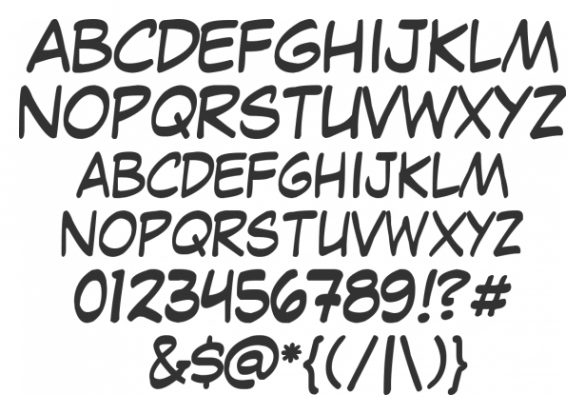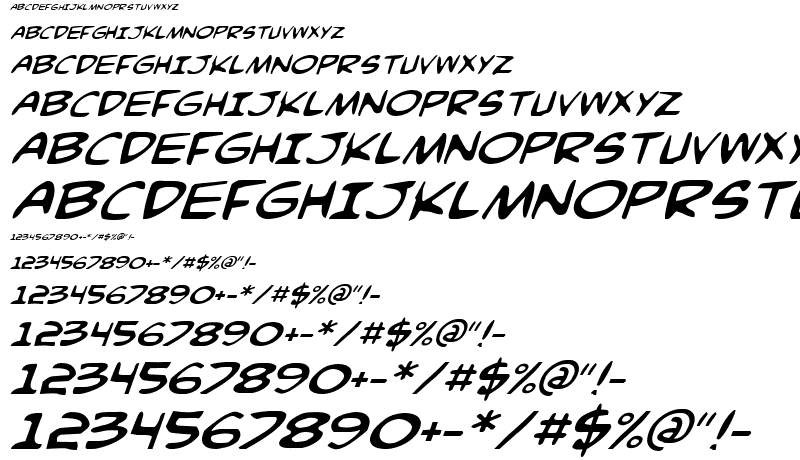
Лучшие шрифты с поддержкой кириллицы для Манги: список
Мы подобрали для вас самые известные 🔝 и популярные шрифты для манги. 📖 Именно эти шрифты используются многими переводчиками 📢 в течение длительного времени, и многие пользователи узнают их 👀 по внешнему виду.
Шрифты для манги или комиксов востребованы всегда. И сколько лет уже существует в интернете направление по переводу манги, столько же есть и вариантов шрифтов.
Хотя зачастую для основных надписей используют всегда одни и те же шрифты, т.к. их читать удобно и выглядят они стильно. Но, например, мысли, восклицания, надписи сюжета, бывает, что пишут разными. Что же до тех художников, кто рисует мангу или комиксы для себя – они используют шрифты разные, те, что ближе по духу и атмосферности.
Шрифт Aqum 2 кириллица
Aqum 2 семья шрифтов из 4 стилей.
Шрифт Bondi кирилица
Шрифт Storytella Cyrillic
Golos
Golos Text — универсальный закрытый гротеск, хорошо подходит для чтения длинных текстов с экрана и рекомендуется для государственных сайтов и социальных сервисов. Golos UI — униширинный гротеск, который благодаря чуть зауженным пропорциям, идеально подходит для использования в элементах интерфейсов. Свойство фиксированной ширины знаков (Uniwidth) позволяет сохранять длину строки, при работе с начертаниями разной насыщенности.
Дизайнеры Александра Королькова и Виталий Кузьмин. Шрифт подготовлен и выпущен компанией Паратайп в 2019 году. Количество глифов 467.
Lack
Это смелый, современный и экспериментальный шрифт, который поставляется в одной насыщенности с курсивом. Он хорошо работает как дисплейный шрифт, но также предназначен для работы с текстами любого размера.
В 3 различных стилистических наборах спрятано множество альтернатив. VTFLack был первоначально создан Адриеном Мидзиком в 2013 году. В 2016 году он начал перерабатывать шрифт, чтобы его можно было использовать в разных графических областях, а не только для экспериментальных работ.
В этой версии есть оригинальные строчными буквы, оптимизирована разборчивость и добавлены контурные начертания. Последнее обновление 2018. Количество глифов 1017.
Bebas Neue
Бебас — самый популярный во всем мире прописной шрифт стал «Гельветикой свободных шрифтов». Выпущенный в 2010 году Bebas Neue используется как крупными компаниями, так и начинающими дизайнерами для многих проектов. Новые начертания остаются верными стилю и изяществу Bebas со знакомыми чистыми линиями, элегантными формами, сочетанием технической прямоты и теплой простоты. Семейство Bebas Neue одинаково уместно для веб, печати, коммерции и искусства.
Ему делают регулярные обновления, а в 2019 вышел долгожданный платный Bebas Neue Pro со строчными буквами и наклонными начертаниями.
Moniqa
Вариативный шрифт с 162 начертаниями разной ширины и контрастности. Начертание Display (с самыми тонкими элементами и сильным контрастом) выглядит изящно и богато в крупном размере, Heading подойдет для заголовков, а Paragraph обладающий наименьшим контрастом — для более мелкого текста. Это многоязычный шрифт с альтернативными символами, стилями, лигатурами и множеством возможностей OpenType.
Идеален для журналов, рекламы и брендинга. Дизайнер Rajesh Rajput. Опубликован на Behance 4 июня 2019 года. Количество глифов 865.
Spectral
Текстовый шрифт, обращающийся к истории французского шрифтового дизайна, но современный и универсальный, хорошо подходящий для чтения с экрана: Spectral разрабатывался в первую очередь как шрифт для Google Docs и Google Sheets — офисных инструментов для совместной работы.
У него характерные для динамической антиквы контраст, открытость знаков и оси овалов. Есть ещё родственный капительный шрифт Spectral SC с таким же набором начертаний.
Кириллица в шрифте качественная и сбалансированная, с хорошо применёнными конструкциями и решениями, нарисована Ильей Рудерманом и Юрием Остроменцким из type.today. Количество глифов 145.
IBM Plex
IBM Plex — шрифты высокого качества, подойдут для широкого спектра применений так как обладают отличной читаемостью в печатных, веб- и мобильных интерфейсах. Кириллица в шрифте сбалансированная, с хорошими конструктивными решениями. Дизайн во многом обращается к истории IBM, цитирует её графические артефакты и в целом пытается отразить роль компании как проводника между человеком и машиной.
Сочетание рационального и эмоционального отражено через контраст между угловато-геометричными и округлыми элементами. Более тонкие детали — вертикальные сегменты внутри овалов, выразительные входы арок и овалов в вертикальные штрихи.
Все составные части находятся в балансе со спокойными внешними контурами. Три дизайна Plex хорошо работают независимо друг от друга, но еще лучше — вместе. Используйте Sans в качестве современного компаньона, Serif — для редакционного повествования, а Mono — для демонстрации фрагментов кода. В зауженном Plex Sans Condensed пока кириллицы нет. В курсивах контраст между жёсткими и округлыми элементами только усиливается, что дает еще больше возможностей.